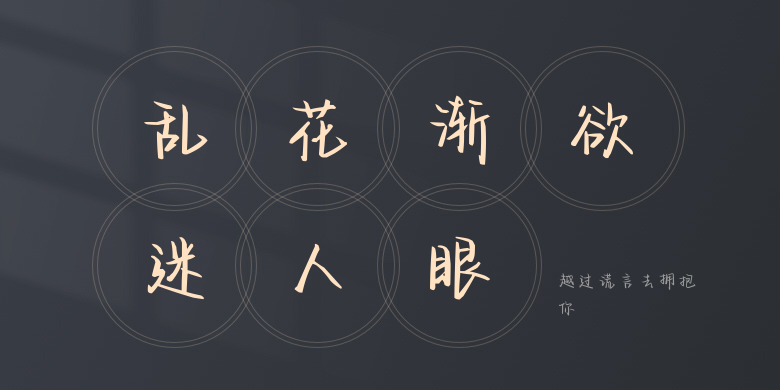
越过谎言去拥抱你
越过谎言去拥抱你,这款字体结构工整、笔画清晰,兼顾美观与易读性,适用于标题、正文、海报、包装、LOGO 等多种场景。字形优雅稳定,风格百搭耐看,适配日常排版与创意设计,让文字呈现更舒适、更具质感。越过谎言去拥抱你一笔一画,皆是细节,以均衡的比例、流畅的线条打造舒适视觉体验,字形端正大气,风格简约现代。无论是商业设计、品牌宣传还是日常排版,都能轻松驾驭,让文字更有格调与力量。越过谎言去拥抱你字体下载。